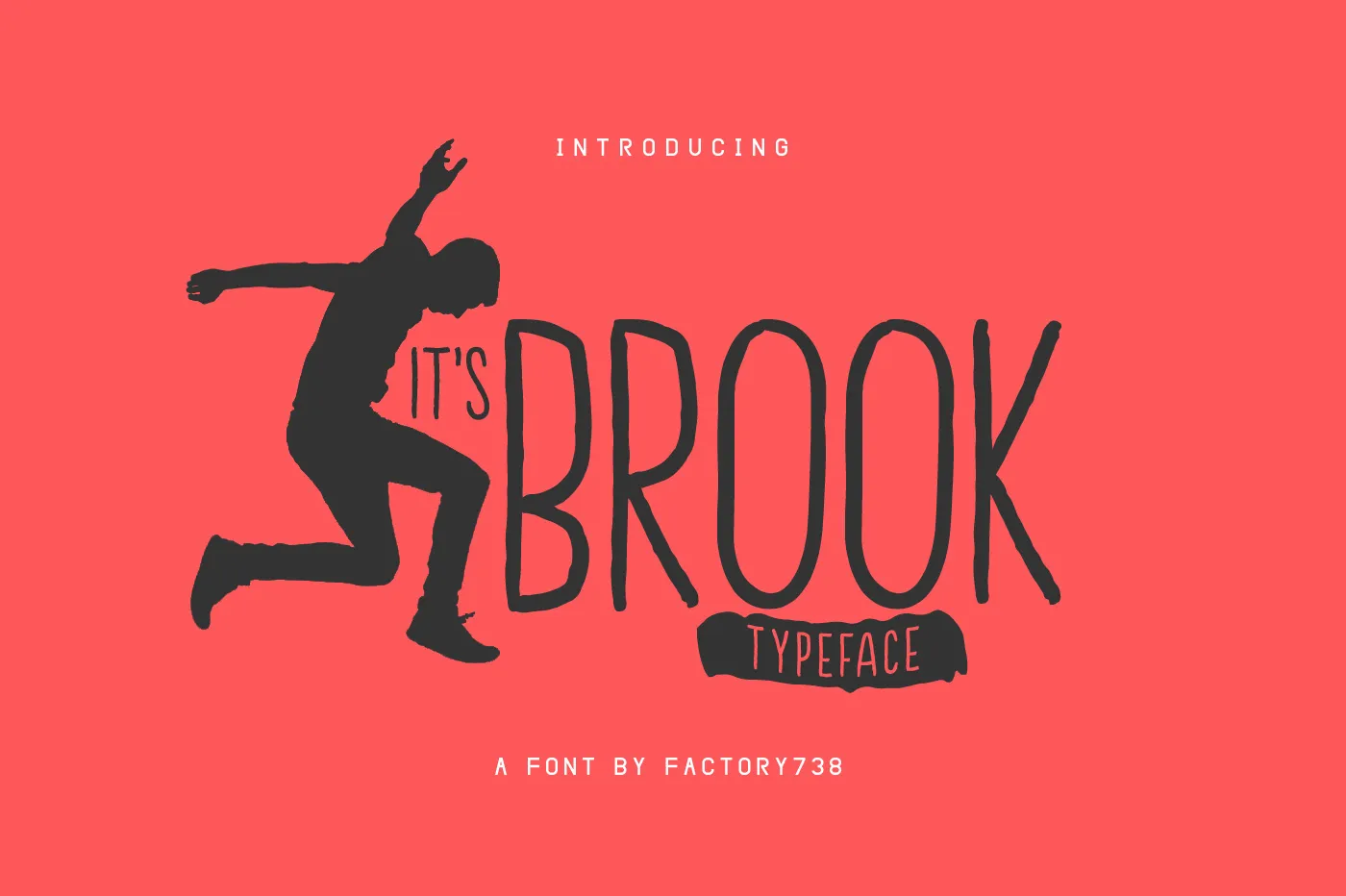
Brook Font – Download Grátis
A Brook Font é uma nova fonte criada pelo designer Factory738. Esta fonte traz a beleza única do trabalho artesanal tradicional. É uma escolha perfeita para o design de convites, cartas de boas-vindas, materiais de marca, cartões de visita, mensagens e posters. Seu formato varia entre 4 pesos diferentes: regular, leve, extra-leve e fino, criando um contraste suave que torna a Brook Font ideal para diversos usos visuais. É uma fonte perfeita para os designers buscando um toque delicado e único em seus projetos. A Brook Font é uma escolha inteligente para quem busca uma fonte de qualidade para projetos que requerem um toque especial de elegância.